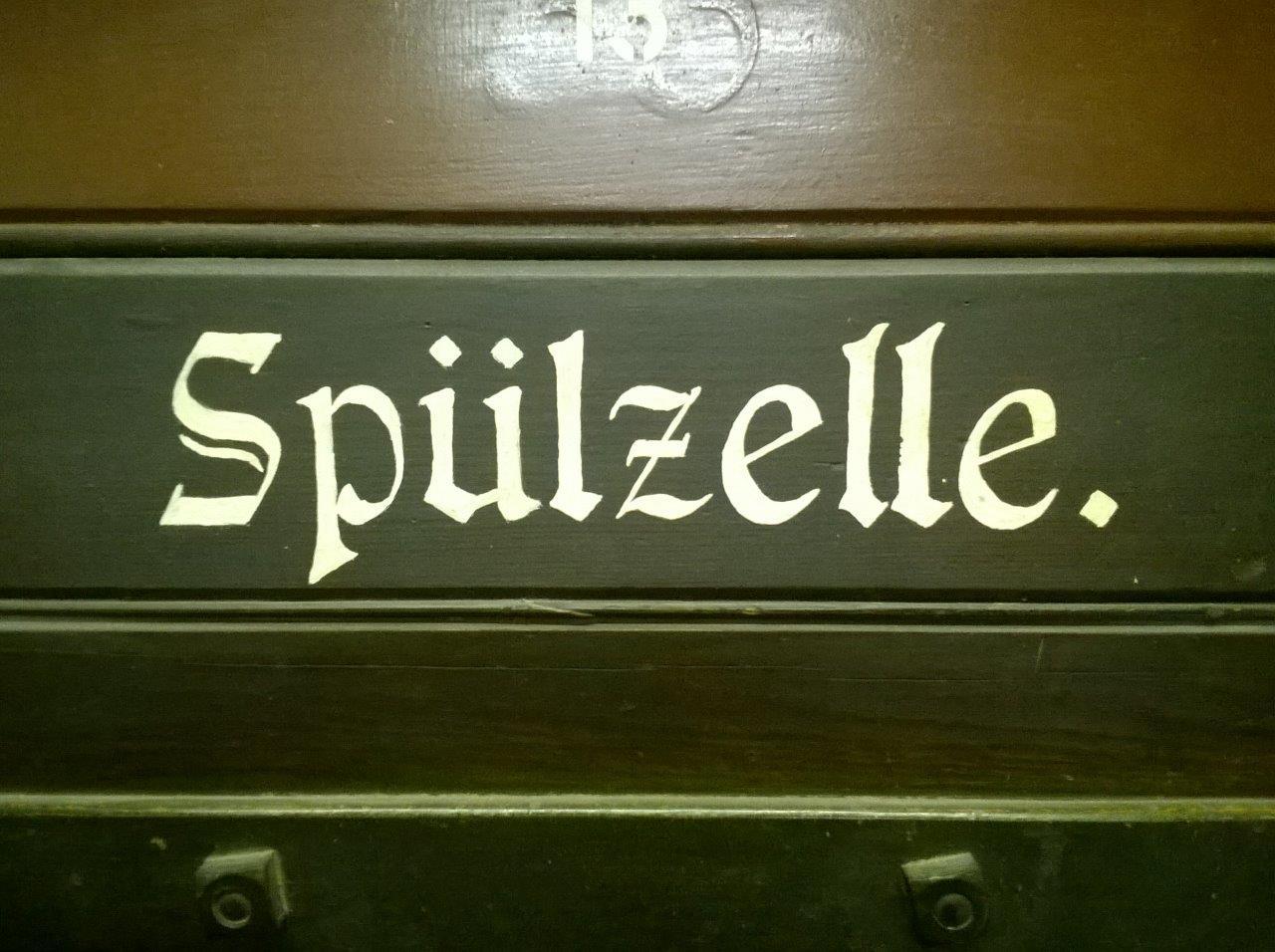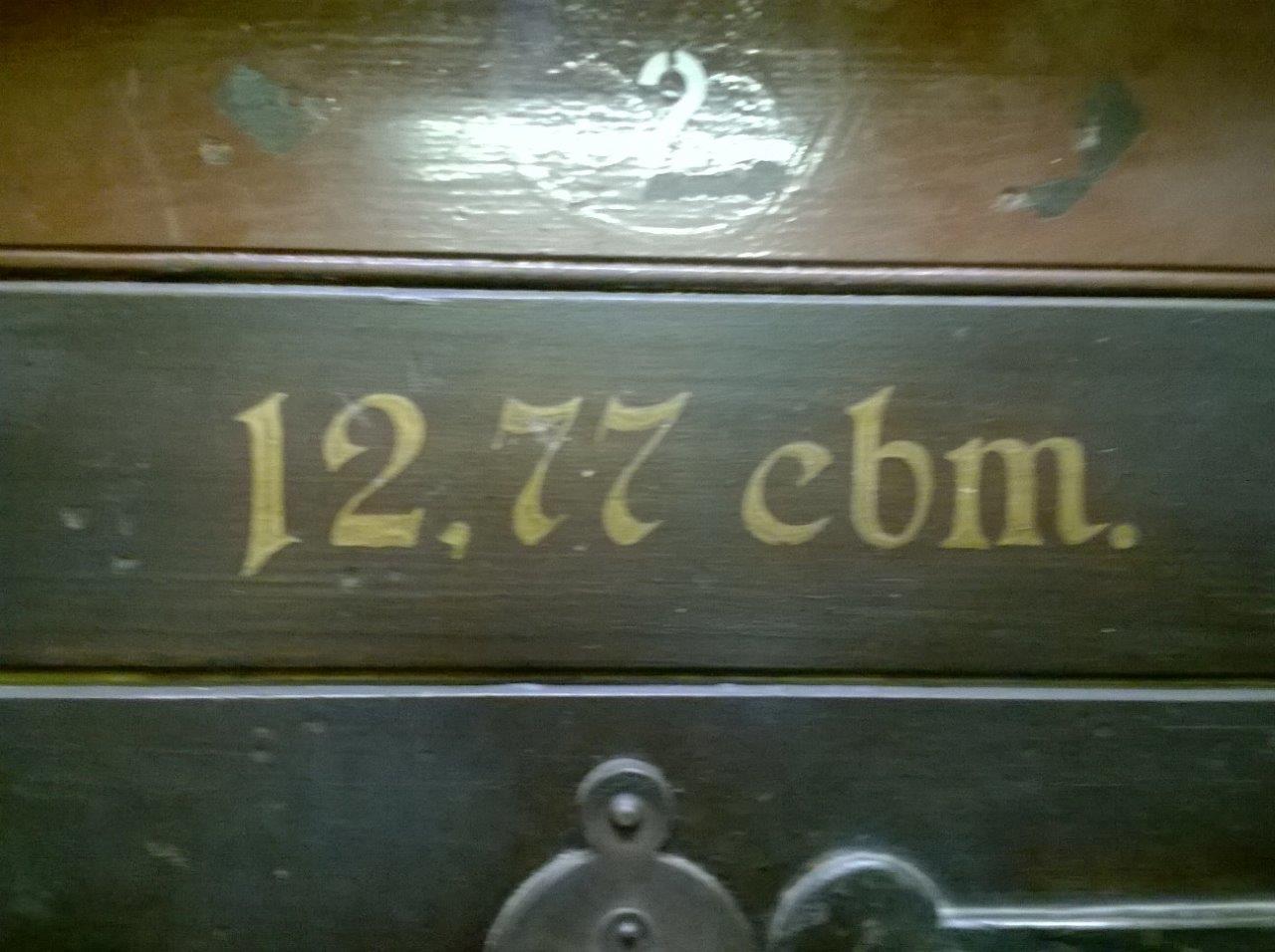
Gefängnis-Schrift
ich habe heute eine Gefängnis-Besichtigung in Hannover gemacht und war ganz fasziniert von den Türbeschriftungen -
aber, um welche Schriftart könnte es sich handeln?
Ja, herrlich! Und ehrlich gesagt, das Gefängnis ist insgesamt eine super Location, vielleicht für einen Film aus damaliger Zeit!
Da wurde echt einiges vermischt: das z will so gar nicht zu irgendwas anderem darin passen und allein das m im zweiten Bild ist ein Mix aus Kursiv und aufrecht (s. Abschlüsse an den Beinen). Auch die e-Formen haben etwas kursives und die Feder-(bzw. Pinsel-)Winkel sind sehr inkonsequent.
Hab’s mal spaßeshalber bei WhatFontIs verfüttert, und das sind ein paar Ergebnisse: